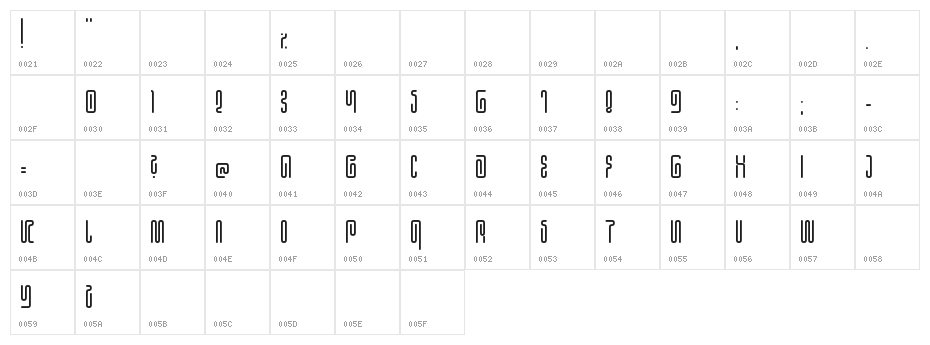
Hieroglyphic Font
| Caso d'uso | Logos, Artistic projects, Themed events |
| Progetti proposti | Ideal for themed events, artistic projects, or creating an exotic and mysterious aesthetic in design work. |